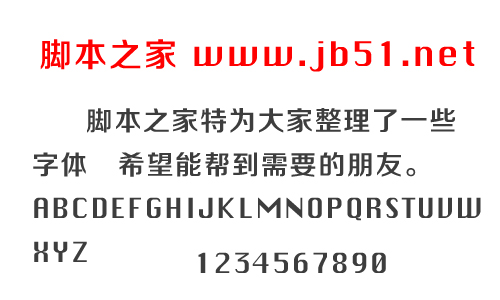
芝加哥正黑體字體是芝加哥正黑系列中的一款常規(guī)字體,該字體筆畫粗細(xì)平均,筆畫平直,其風(fēng)格雄強(qiáng)正肅,引人注目,能夠應(yīng)用于文本裝潢、信息展示、網(wǎng)頁設(shè)計(jì)、篆刻制模、數(shù)據(jù)制作、裝潢設(shè)計(jì)、計(jì)算藝術(shù)設(shè)計(jì)、視覺設(shè)計(jì)、字帖等一切合法應(yīng)用場(chǎng)景。歡迎大家前來下載。